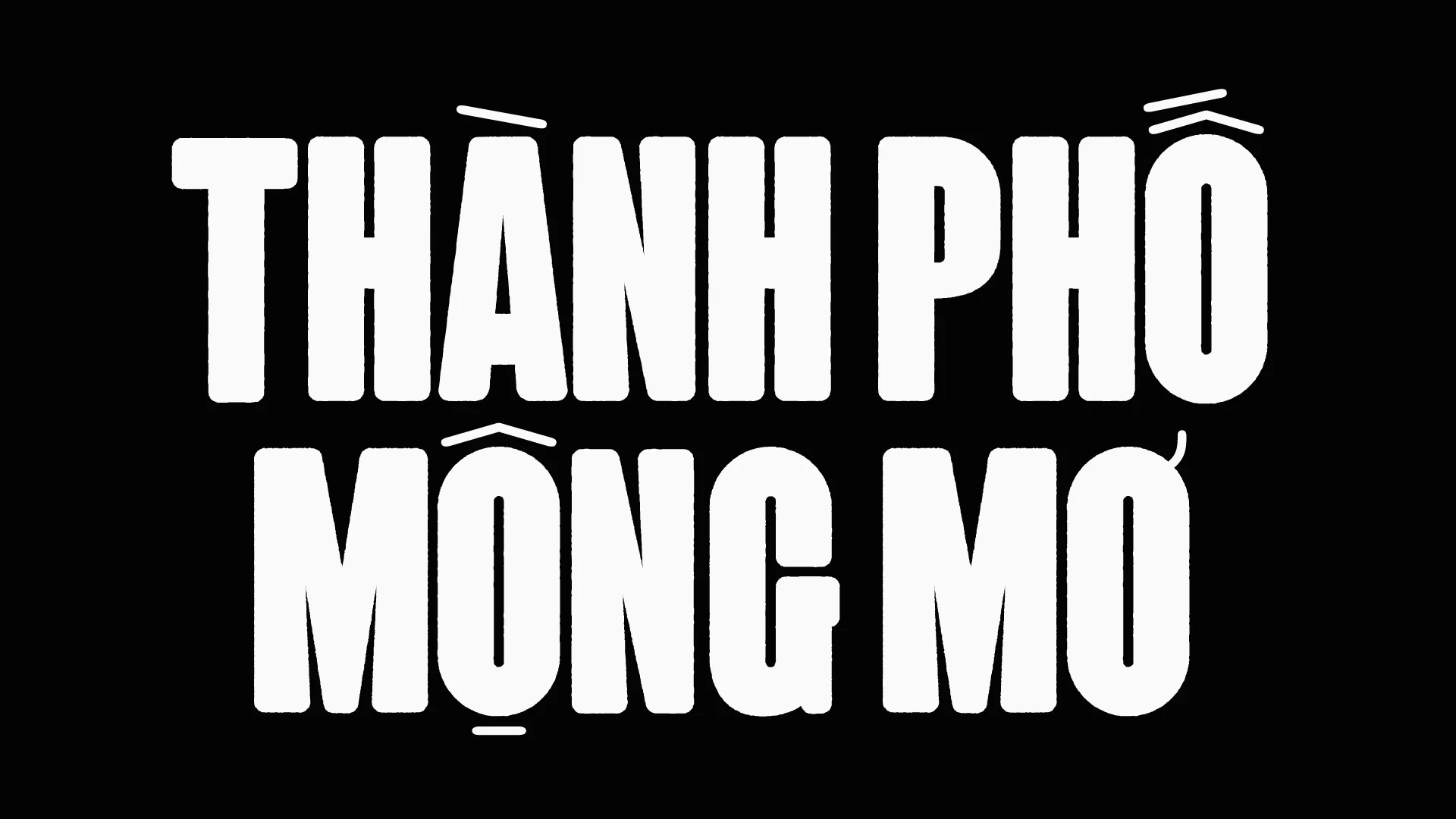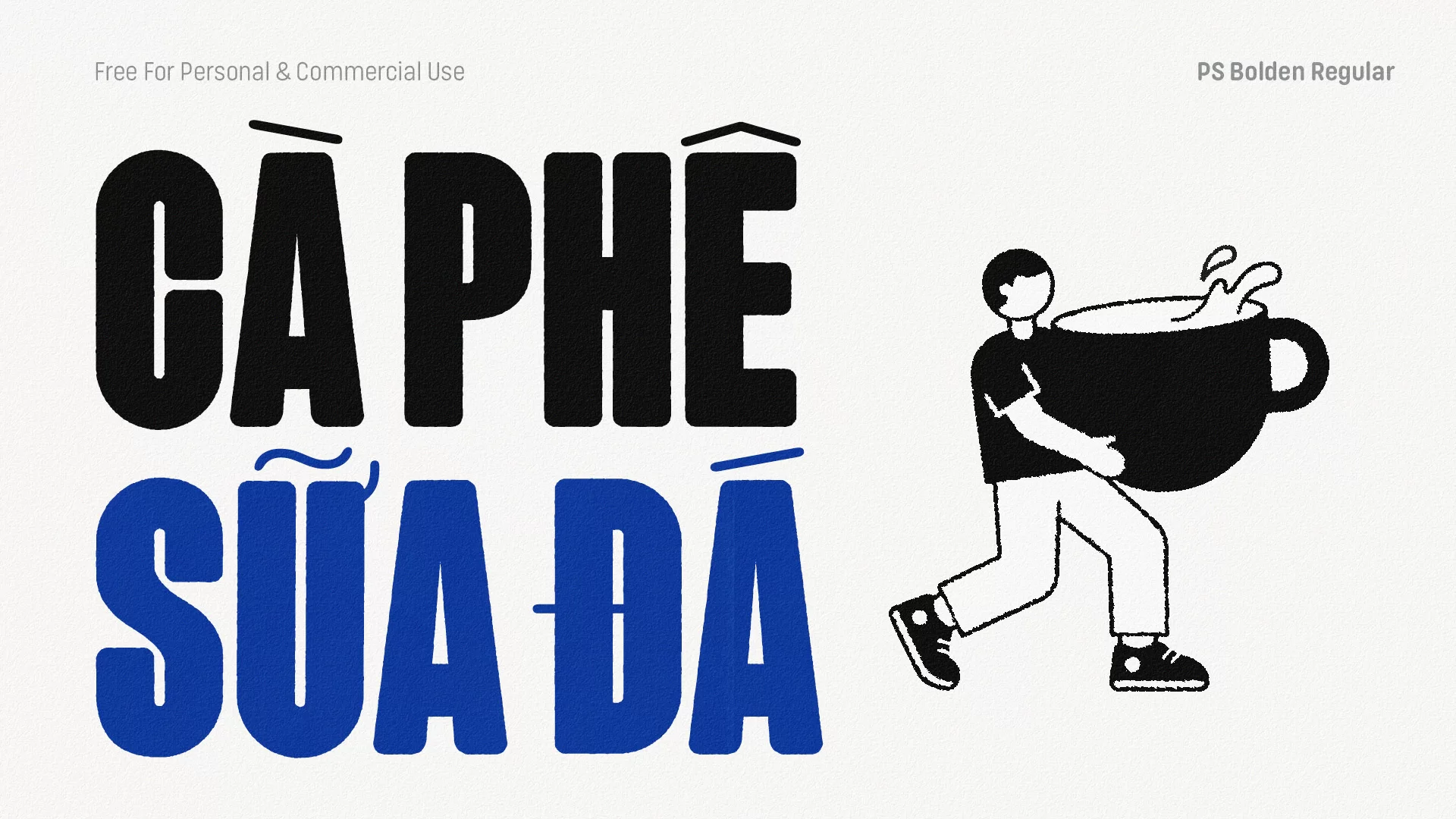
PS Bolden – Font Display Việt Hoá tốt cho tiêu đề
Bolden lấy cảm hứng từ kỹ thuật in ấn thủ công cũ. Là một font All-Caps (chỉ có chữ in hoa). Bộ chữ sở hữu các đường nét dày, các góc chữ được bo tròn tạo cảm giác thân thiện nhưng vẫn có những phần cạnh thô ráp, gai góc nhẹ để giữ lại cái hồn của chất liệu in ấn vintage. Các khoảng trống bên trong chữ được thu lại tối đa, kết hợp với khoảng cách giữa các chữ rất chặt. Điều này tạo ra một khối chữ đặc, nặng và có tính hút mắt cao.